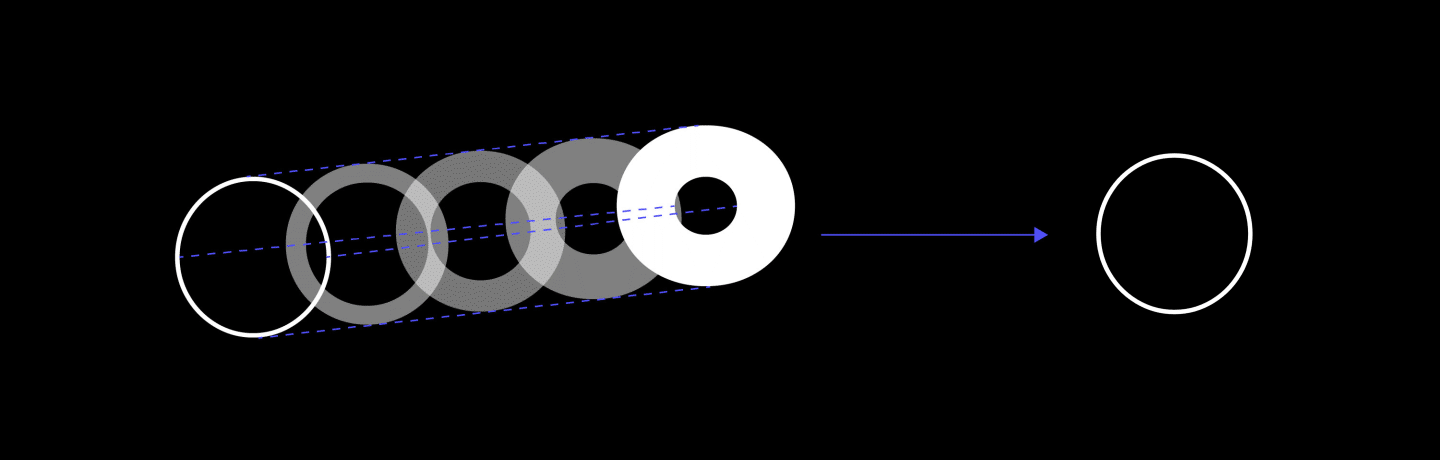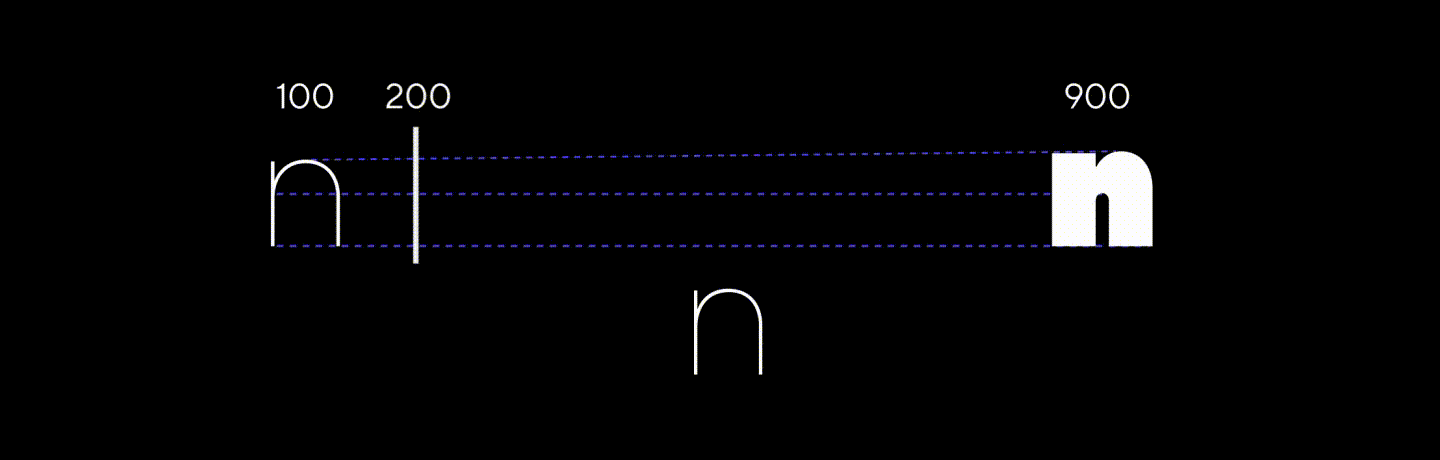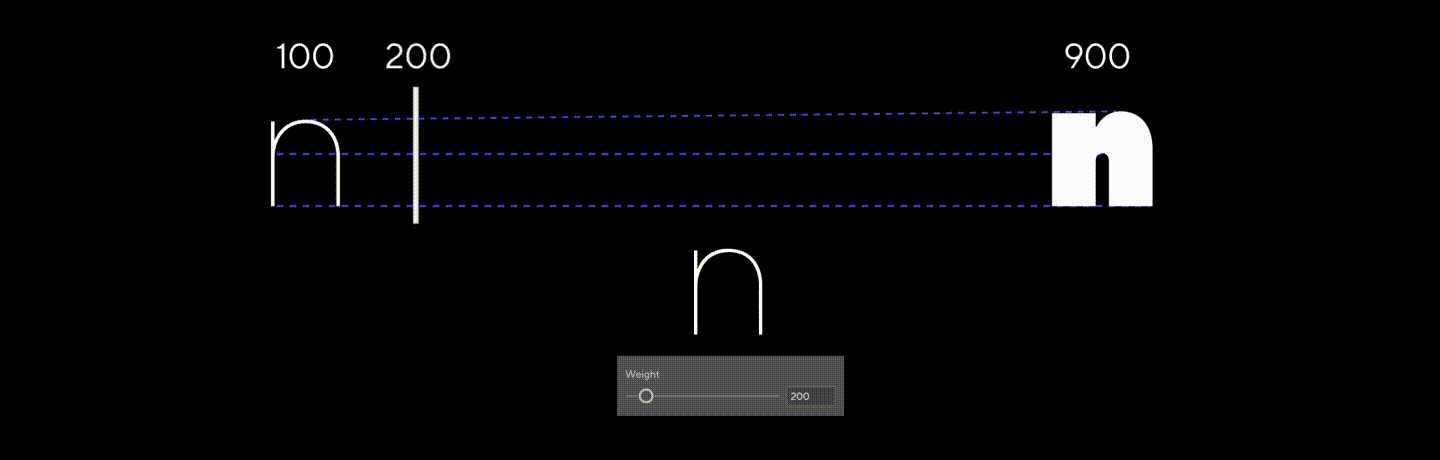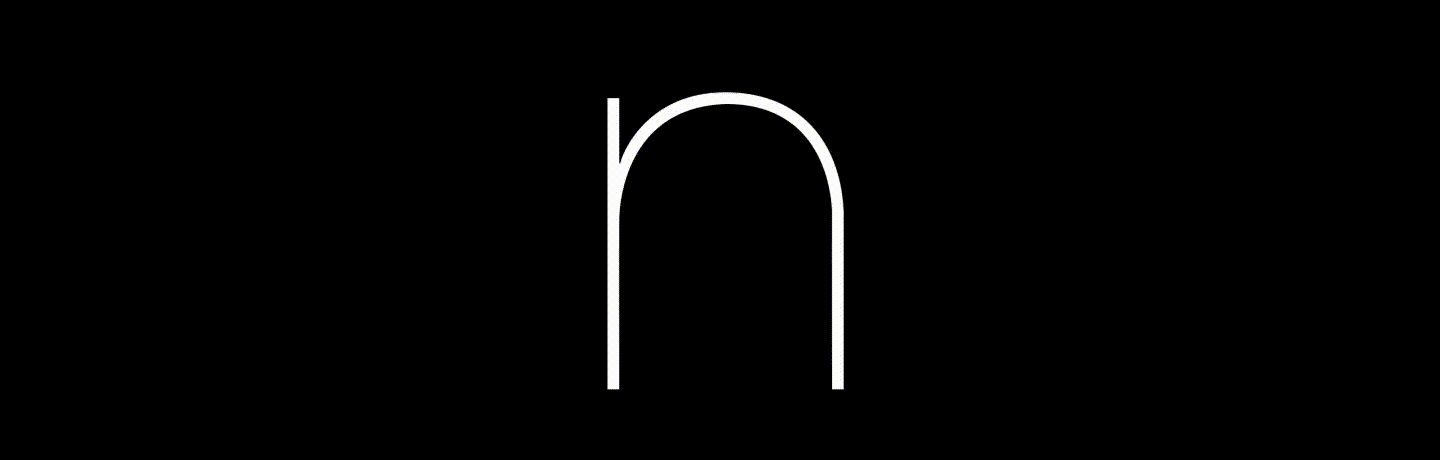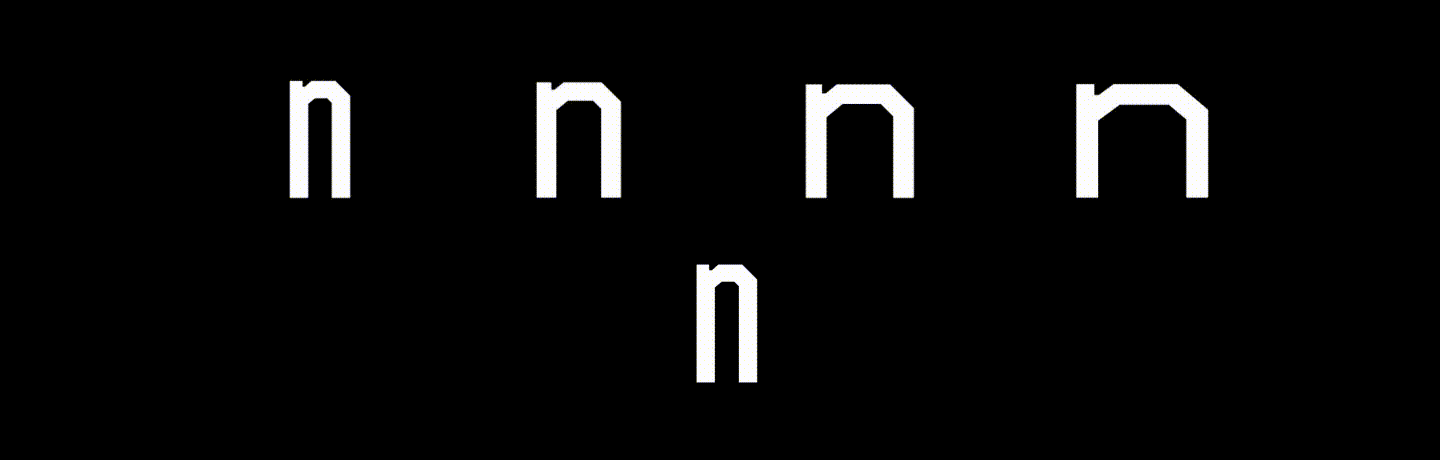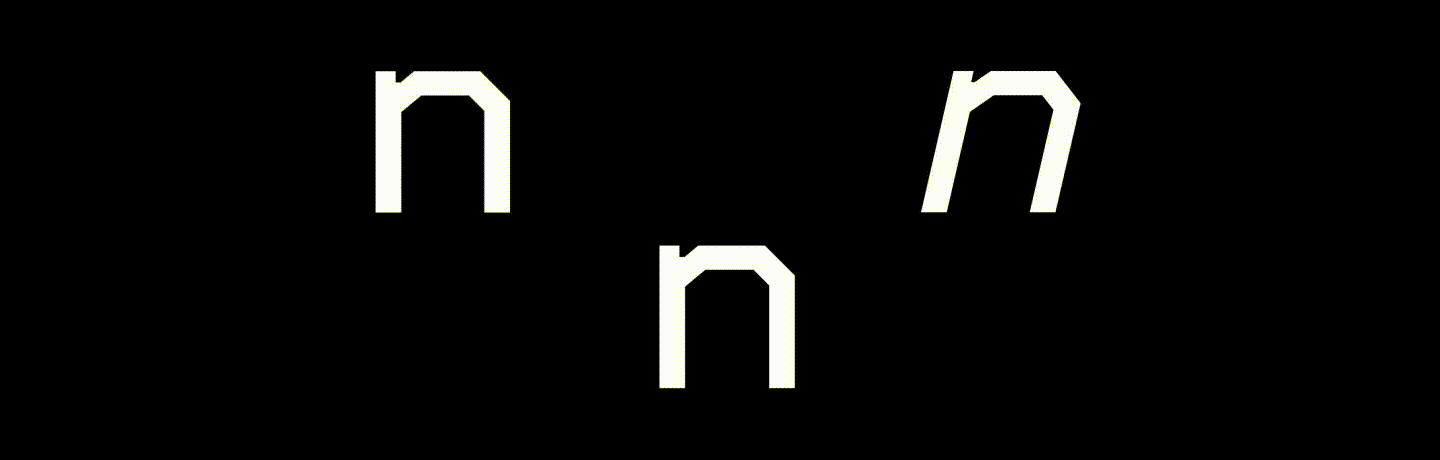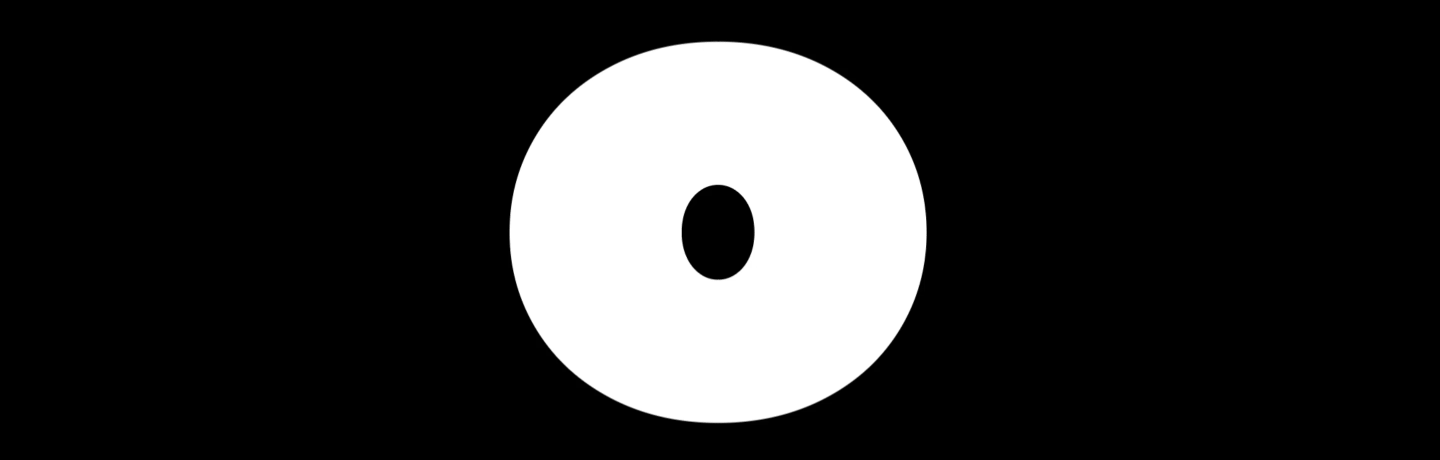
Вариативные шрифты: что это и как использовать?
Вариативные шрифты
В этой статье расскажем о вариативных шрифтах — насколько это интересный, полезный инструмент, но недооцененный одновременно. О минусах и нюансах работы с ними также не забудем упомянуть.
История возникновения
Для начала, чтобы ввести вас в курс дела, расскажем об истории развития шрифтовых технологий.
Во второй половине 80-х годов XX века были представлены форматы PostScript компанией Adobe и TrueType компанией Apple для разработки шрифтовых файлов. Оба они использовали кривые безье для построения знаков. Этими форматами в обновленном виде мы пользуемся и по сей день при работе над шрифтовыми файлами.
1980s — PostScript (Adobe), TrueType (Apple)
1980s — PostScript (Adobe), TrueType (Apple)
В 1991 году компанией Adobe была представлена технология Multiple Master как расширение формата PostScript, которая позволяла хранить в одном шрифтовом файле несколько вариантов контура для одного глифа. Эти варианты были крайними точками на оси, между которыми можно было найти промежуточные значения, например, изменить вес или ширину.
1991 – Multiple Master (Adobe)
1991 — Multiple Master (Adobe)
Чтобы пользоваться таким шрифтом, сначала нужно было сгенерировать статичное начертание с помощью специальной программы (Adobe Type Manager) и после этого загрузить его в систему, чтобы использовать в графическом редакторе. Из-за сложности использования этот формат так и не стал популярным, а шрифтовые дизайнеры продолжили выпускать статичные начертания.
Статичное начертание
В 1997 компаниями Adobe и Microsoft совместно была представлена технология OpenType. Она основывалась на формате TrueType, но включала в себя возможность внедрить заметно большее количество знаков (65000, ранее лимит был 256), а также OpenType фичи, без которых мы не представляем сейчас современный шрифт. Здесь речь идет, например, о поддержке капители, табулярных знаков, супериоров, стилистических сетов, контекстных альтернатив и т.д. OpenType формат и по сей день является самым популярным.
И, наконец, в 2016 году Adobe, Apple, Google и Microsoft анонсировали новую версию формата OpenType — OpenType Font Variables. С этого момента шрифтовые дизайнеры имеют возможность заложить информацию о нескольких начертаниях шрифтового семейства в один файл. Суть этого формата похожа на Multiple Master с одним принципиальным отличием — теперь не нужно заранее генерировать статичные начертания. Параметры можно подбирать прямо в графическом редакторе.
2016 — OpenType Font Variables
2016 — OpenType Font Variables
Технические особенности
Давайте остановимся подробнее на том, чем же этот формат отличается от классического OpenType.
Когда дизайнер приобретает какое-то шрифтовое семейство, допустим, гротеск, состоящий из 9 толщин, у него в распоряжении появляются 9 отдельных шрифтовых файлов. Эти начертания были заранее подготовлены шрифтовым дизайнером, развесовка была рассчитана таким образом, чтобы толщины были распределены равномерно от самой тонкой до самой жирной.
TT Norms® Pro
TT Norms Pro
Вариативный шрифт представляет собой один файл, разброс начертаний в котором ограничен только самой тонкой и жирной толщиной. Между ними дизайнер может самостоятельно выбрать любое понравившееся положение.
TT Norms® Pro Variable
TT Norms Pro Variable
Если заглянуть внутрь шрифта, то у каждого знака есть опорные точки, по которым он строится. И, если количество этих точек одинаковое в тонком и в жирном начертаниях, программа может их соединить и просчитать промежуточные положения точек. Конечно, разработка шрифта не так проста и прямолинейна и зачастую нам приходится задавать больше двух опорных начертаний, но на пользовательский опыт это никак не влияет.
Опорные начертания
Разброс между двумя крайними начертаниями называется осью. В графических редакторах, например Adobe она выглядит как отрезок с ползунком, который можно передвигать, подбирая нужное значение.
Ползунок в графическом редакторе
Ползунок в графическом редакторе
Варианты осей вариативности:
Первый вариант — это уже описанная ось толщины. В большинстве шрифтовых семейств есть несколько начертаний по толщине и в теории они все могли бы быть вариативными.
Weight axis
Представим ситуацию, что вы купили обычное шрифтовое семейство и планируете его использовать для того, чтобы сверстать книгу или сайт с большим объемом текста. Вы знаете, какая толщина основного текста должна быть, чтобы пользователю было комфортно его читать. Но вдруг возникла проблема — регулярное начертание в семействе вам кажется слишком светлым, а следующее по толщине, скажем, медиум, — слишком жирным. Идеально подошла бы промежуточная толщина, но такого варианта нет. Если бы этот шрифт был вариативным, то все, что нужно было сделать, это сдвинуть ползунок в графическом редакторе или выставить кастомное значение CSS в коде сайта в промежуточное положение между этими двумя начертаниями.